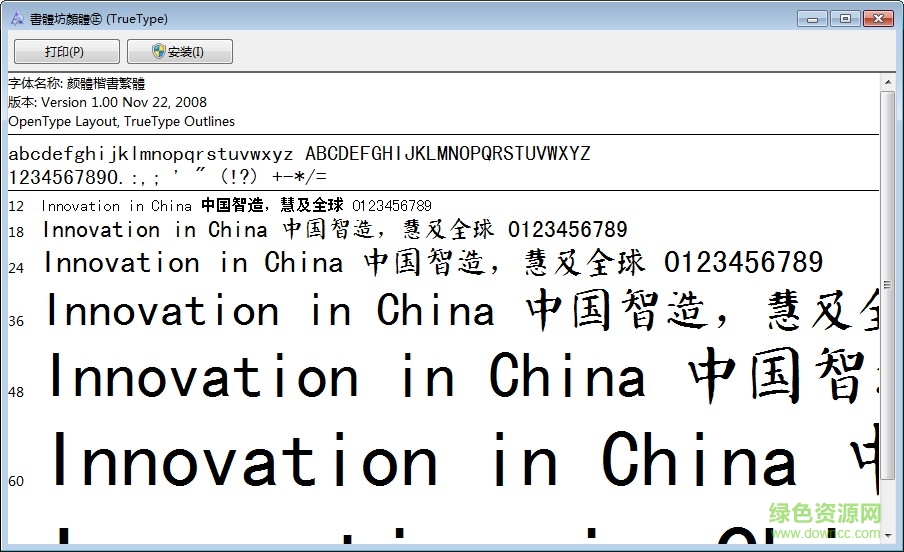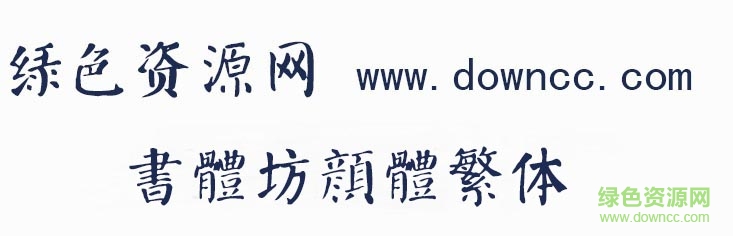
軟件介紹 軟件標簽: 書體坊字體 字體 書體坊顏體繁體是一款應用較廣的書體坊字體,字體線條較粗,字形飽滿端正,印刷效果非常醒目,喜歡該字體的小伙伴歡迎在綠色資源網下載!書體坊顏體繁體使用說明:Win XP(2000\98)系統(tǒng) : 把解壓好的字體文件放入 C:\Windows\Fonts 目錄中即可蘋果(APPLE)Mac OS系統(tǒng) : 下載好后雙擊字體,然后選擇:安裝字體Win 7\Win 8\Win 10系統(tǒng) : 鼠標右鍵單擊字體文件,然后點擊 > "Install" 安裝字體注意事項:本站所有字體資源僅供個人學習與參考,如需商業(yè)使用請到相關官網授權。 軟件截圖 上一張下一張(1 / 1) 安裝詳細截圖 猜你喜歡 繁體字體 顏體字體 繁體字體 繁體字體有哪些?小編今天為大家推薦幾款好看的繁體字體,包含了繁體鋼筆字體、繁體隸書字體、繁體毛筆字體、繁體行楷字體等不同類型的繁體字體!廣告、PPT、海報、雜志等領域都可使用! 查看更多>> wow魔獸世界臺服字體包 2.40M/中文/0.0/ttf免費版下載 繁體書法字體 3.41M/中文/6.6/下載 楷書繁體字體包 9.76M/中文/8.0/下載 隸書繁體字體 5.46M/中文/4.2/.ttf下載 茶碗古刻繁體 5.37M/中文/5.0/下載 hyx4gf regular 3.41M/中文/8.0/下載 顏體字體 顏體是一款極具古樸厚重韻味的字體,這里匯集了各具特色的顏體字體,每款字體都有著顏體豐腴雄渾、骨力遒勁的魅力,因此顏體也深受廣大書法家的喜愛,下面有綠色資源網小編為大家提供顏體字體下載大全,感興趣的朋友歡迎來綠色資源網下載體驗! 查看更多>> 經典簡顏體字體 2.44M/中文/1.2/下載 tianshi-yanti字體 2.92M/中文/5.0/下載 全真顏體簡體字體 4.88M/中文/2.5/下載 fashionfont052 by字體 2.44M/中文/2.0/下載 刻石錄顏體字體 8.53M/中文/5.7/下載 顏體字體下載大全 52.01M/中文/1.6/ttf下載 其他版本下載 標題 大小 更新日期 下載 下載地址 電腦版 書體坊顏體繁體字體 點擊報錯 軟件無法下載或下載后無法使用,請點擊報錯,謝謝! 關閉報錯反饋 請描述您所遇到的錯誤,我們將盡快予以修正,謝謝! *必填項,請輸入內容 本類最新 首爾南山體字體 v1.06 官方版 潮字社風云簡ttf 潮字社凌渡鯤鵬簡體字體 潮字社曾玉波手書簡字體 微博慧心字體 阿里巴巴iconfont字體庫 相關文章 Photoshop字體安裝使用方法和技巧 如何解決“無法新增字體”問題 Win 7系統(tǒng)安裝字體方法 網頁字體大小設置方法 怎么改網頁字體大小 在Linux系統(tǒng)中安裝字體的幾種方法 windows7字體顯示問題:打開某些程序的時候顯示的是亂碼 用戶評論 熱門評論 最新評論 發(fā)表評論 查看所有評論(0) 昵稱: 請不要評論無意義或臟話,我們所有評論會有人工審核. 字數: 0/500 (您的評論需要經過審核才能顯示)